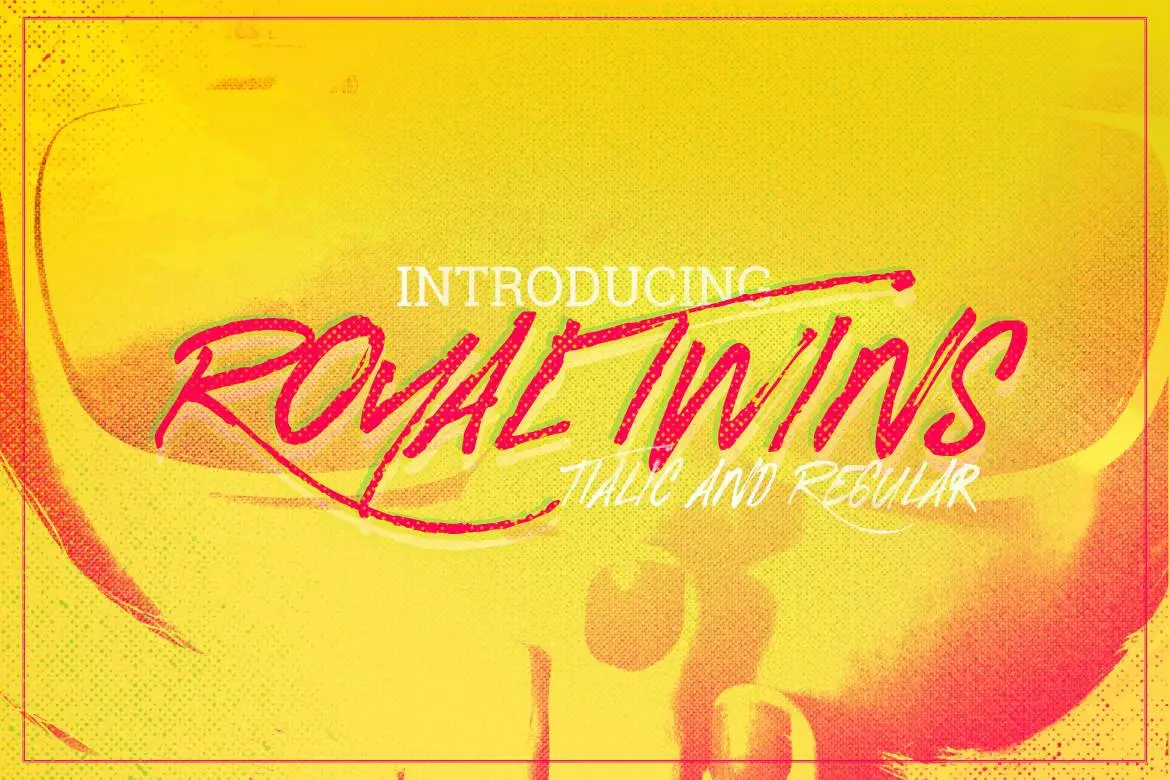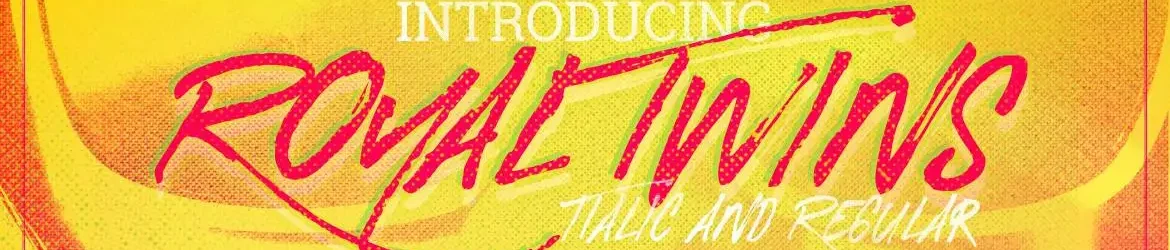
Estamos muito felizes por você explorar a Royal Twins Brush Font, uma nova e moderna tipografia que combina graça com força. Especialmente projetada para designers visuais, esta fonte é o resultado de criatividade compartilhada entre LeoSupply.co. Com Royal Twins, encontrará uma fonte brush totalmente central europeia, disponível em versões regular e inclinada. Perfeita para expressar mensagens fortes, este script-font vibrante oferece rápidação nos traços e aguçadas bordas. A Royal Twins é perfeitamente adaptada para criações como logotipos, tags de nome, citações escritas a mão, embalagens de produtos, materiais de merchandising, mídia social e cartões de cumprimentos. Seja você um designer gráfico ou criador de conteúdo digital, Royal Twins é uma fonte indispensável para qualquer projeto que exige estilo elegante com energia.